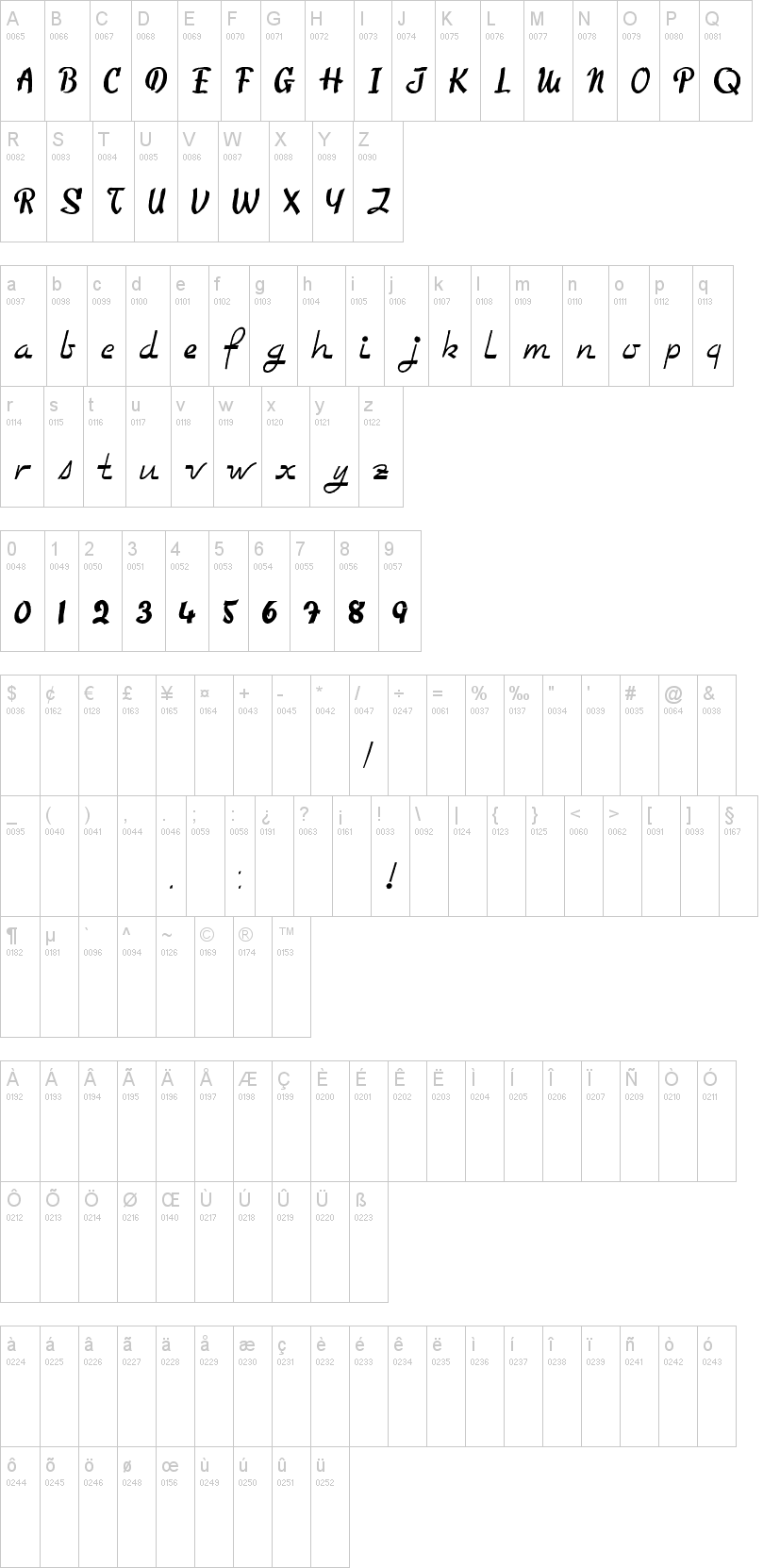
Too Good To Be True 是一款新的手写体字体,由著名的设计师Rocío Heredia创作。该字体具有温暖、柔和的外观,适合用于婚礼、浪漫等场合的设计。它的字体设计结合了传统的手写体字体和卡通字体的特点,使用起来更加轻松,能够更好地表达出情感和气氛。内容介绍
Too Good To Be True是一款非常不错的手写艺术字体,具有很好的视觉感,适合于文化类的宣传设计、商业类品牌的广告和产品包装设计以及个性化文字排版等较多场景。